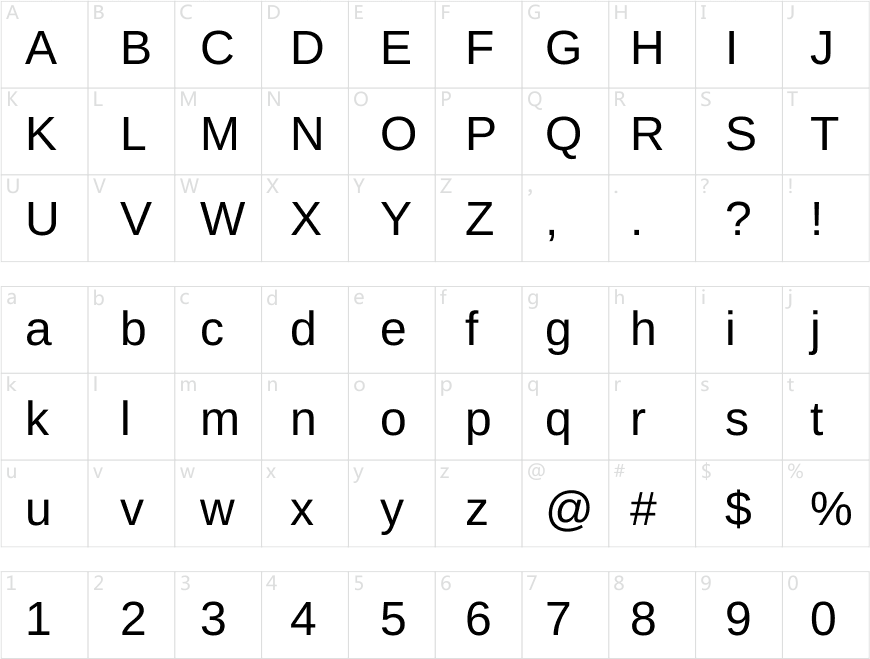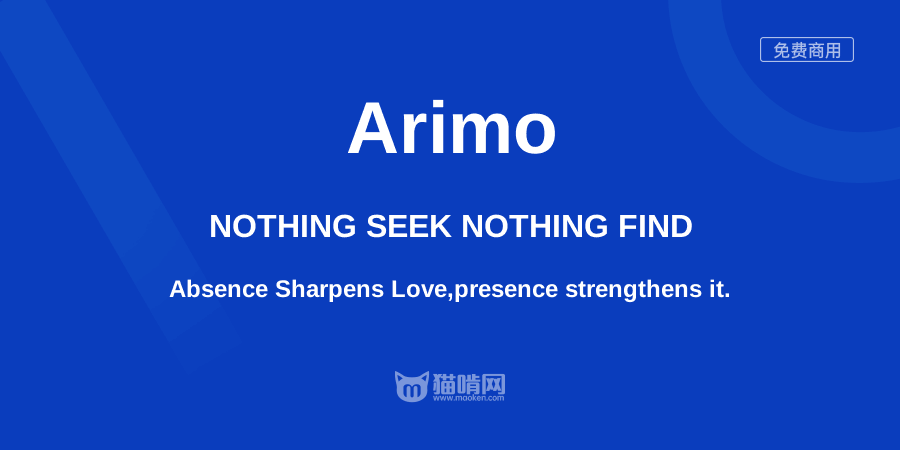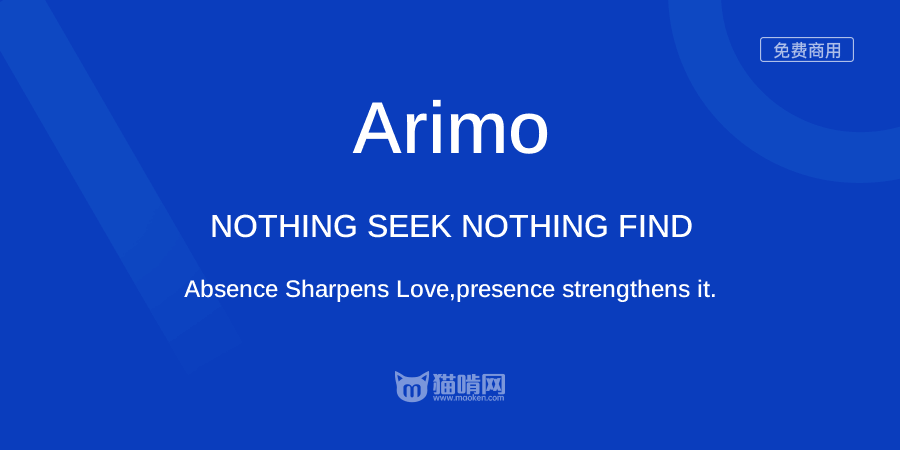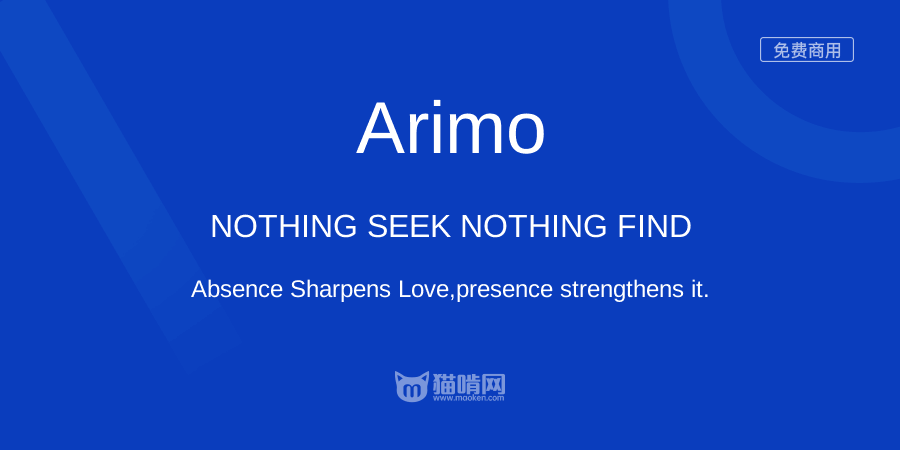
Arimo
字体作者:Steve Matteson (外国) 字体字重:4个
Arimo由Steve Matteson设计,是一种创新的,令人耳目一新的无衬线设计,与Arial™兼容。Arimo提供了改进的屏幕可读性特征和泛欧洲WGL字符集,并解决了开发人员寻找宽度兼容字体以解决跨平台文档可移植性的需求。